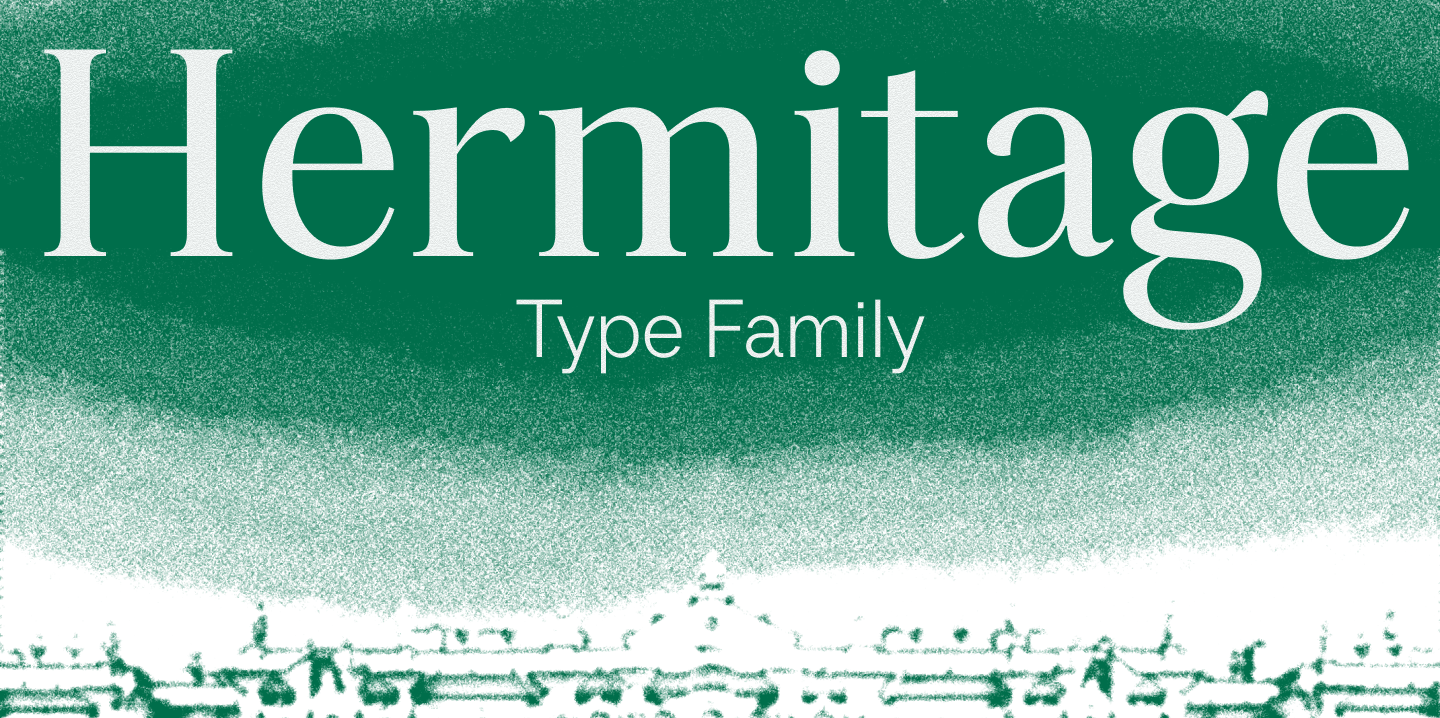
Изучение шрифтовой истории Эрмитажа
Итак, перед нами стояла интересная и очень ответственная задача — разработать шрифтовую гарнитуру для Государственного Эрмитажа. И для того чтобы понять, как она должна выглядеть, мы прошли достаточно большой путь.
Мы знали, что у Эрмитажа богатейшая шрифтовая история, и выбор современных шрифтов для работы в музее так или иначе зависит от неё. Например, активно использовалась старостильная антиква Cormorant. Также у музея был проект по созданию своей кириллицы для шрифта Ingeborg. Однако даже в комплекте эти два шрифта не закрывали все необходимые задачи. Кроме того, оба они имеют достаточно сильный исторический бэкграунд — и в графике, и в плане эмоциональной окраски. Соответственно, нейтральными их назвать нельзя.
«С одной стороны, нейтральность для шрифта — это хорошо, потому что эта характеристика делает его многофункциональным. Таким шрифтом можно оформлять документы, использовать его в приложениях и на сайтах. Но в то же время нейтральные шрифты несколько безликие. А Эрмитажу, конечно же, хотелось свой собственный шрифт, который будет отражать его ценности, его многовековую историю».
Марина Ходак, дизайн-лид TypeType
Поэтому нам предстояло создать такой шрифт, который будет сочетать и исторические отсылки, и универсальность. Было важно, чтобы он подходил для разных задач — от оформления материалов для выставок с привязкой к разным эпохам до использования в коммуникациях.
Одним из важнейших (и к тому же самым узнаваемым) воплощением образа Эрмитажа в шрифте служит логотип музея. К нему мы и обратились в поисках источника вдохновения. Так, в его основе лежит классицистическая антиква с зауженными пропорциями и характерными формами. Узнаваемые детали логотипа — пламевидный язык у буквы «Э», длинные вертикальные засечки и изогнутые ножки у «Ж». Дескриптор же набран шрифтом Times.
Опираясь на эти знания, мы перешли к подбору шрифтов из коллекции TypeType для кастомизации.
Подбор шрифтов для кастомизации
Для начала мы попробовали подобрать шрифт, подходящий к логотипу, — на замену Times. Выбрали пять вариантов: TT Livret, TT Fellows, TT Ricordi Marmo, TT Wellingtons, TT Knickerbockers. Шрифты были подобраны исходя из разной логики и с перспективой развития. Например, TT Knickerbockers прекрасно сочетался с логотипом по ритму — можно представить, что это ряд колонн в одном из музейных залов. А TT Ricordi Marmo сочетает в себе элементы гротеска и антиквы. Нам показалось, что это хорошая аллегория всеобъемлющего шрифта. Вместе с командой Эрмитажа мы смотрели, как каждый из этих шрифтов выглядит в макетах, и обсуждали, какой из них лучше подходит для кастомизации. В результате остановились на TT Livret — функциональной классицистической антикве, включающей дисплейное и текстовое начертания.
С этим шрифтом мы и продолжили работать. Точкой опоры для нас стал логотип. Мы стремились поддержать существующую графику и создать визуальную связь между логотипом и шрифтом, но не буквально повторять элементы, а сделать мягкое взаимодействие, которое будет считываться интуитивно. При этом стоит понимать, что это более глобальная задача, чем кажется изначально.
«Например, в букве „Э“ в логотипе есть характерный изогнутый язык и колючая верхняя засечка. При этом в TT Livret эти элементы совсем другие. Значит, нам нужно перерисовать эту букву, и на другие буквы это тоже повлияет. Если мы меняем засечки в „Э“, они меняются во всех похожих знаках. Мы не можем просто перерисовать три буквы, нам нужно перерисовать практически все знаки, где есть похожие элементы. Кроме того, как только мы начинаем менять какие-то детали, буквы перестают гармонично взаимодействовать друг с другом — значит, нам нужно дополнительно проработать пропорции и сбалансировать шрифт».
Марина Ходак, дизайн-лид TypeType
Так, мы добавили в TT Livret несколько деталей из логотипа — «Ээ» с пламевидным языком, «А» с завышенной средней линией и «Жж» с изогнутыми ножками. В пару к нему подобрали неогротеск TT Neoris, над кастомизацией которого тоже начали работать. Эти два шрифта уже отлично работали в паре и выглядели сбалансировано благодаря схожим вертикальным пропорциям. Мы взяли их за основу и после всех согласований перешли к самому интересному — поиску индивидуального стиля эрмитажного шрифта.
Создание «эрмитажного стиля»
Нашей задачей было создать гармоничную и функциональную шрифтовую пару из дисплейного и текстового шрифтов. Дисплейная антиква (на основе TT Livret) — для работы там, где музею нужно показать свой голос и характер, и функциональный гротеск (на основе TT Neoris) — более нейтральный и читаемый в массиве текста, для решения практических задач.
Первое, что нам нужно было скорректировать в TT Livret, — это контраст. Нужно было сделать его ярче, чтобы привести шрифт к более торжественному звучанию и добавить дисплейности.
Всего в TT Livret есть три подсемейства: Text, Subhead и Display. Мы, конечно, хотели работать со всеми. Но из-за ограниченных ресурсов пришлось идти в направлении «дисплейная антиква + функциональный гротеск». TT Livret при этом мы довели до той степени контраста, который нравился клиенту. Команда Эрмитажа, помимо прочих, тестировала шрифт TT Tsars и попросила нас сделать антикву с таким соотношением тонких и жирных штрихов. Это решение стало окончательным для понимания того, что мы делаем именно заголовочный, титульный шрифт, а не текстовый.
В начале общения нам было важно договориться об общем направлении, чтобы сделать первый шаг. Поэтому мы прописали несколько пунктов, которые казались логичными для старта:
Шрифты будут использоваться во всех цифровых проектах Эрмитажа, отражая историю и ценности музея и задавая тон коммуникации.
«У нас было несколько эрмитажных шрифтов. Некогда, в 1920-х годах, значительная часть научных сотрудников Эрмитажа умела набирать шрифты — Иосиф Абгарович Орбели тоже. Один такой набранный текст, посвящённый заседанию памяти Алишера Навои, лежит в Архиве. Этот сборник был набран во время войны. Так что это важная эрмитажная традиция, когда шрифт становится частью памяти Эрмитажа».
Михаил Пиотровский, генеральный директор Государственного Эрмитажа